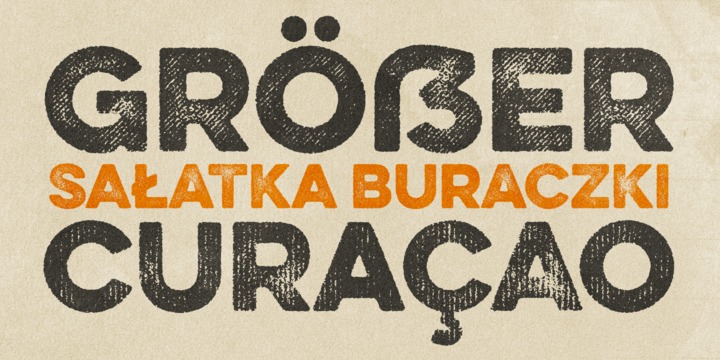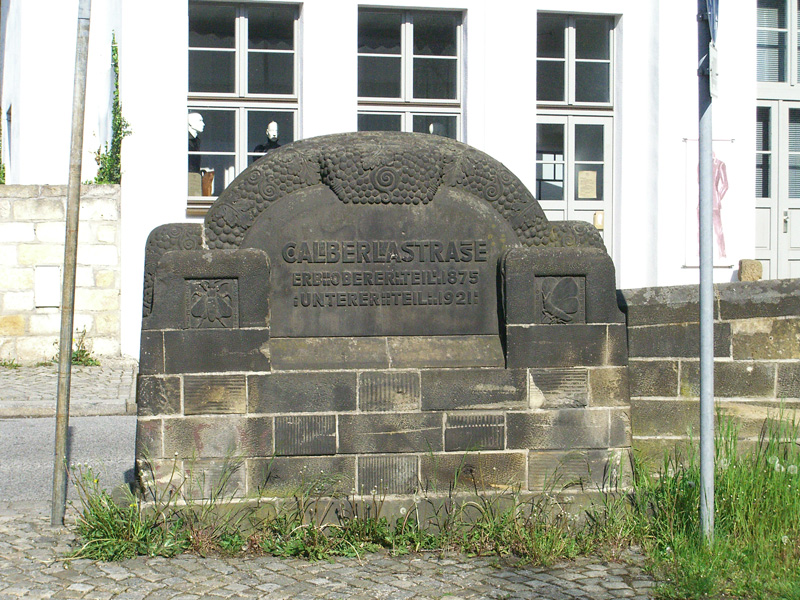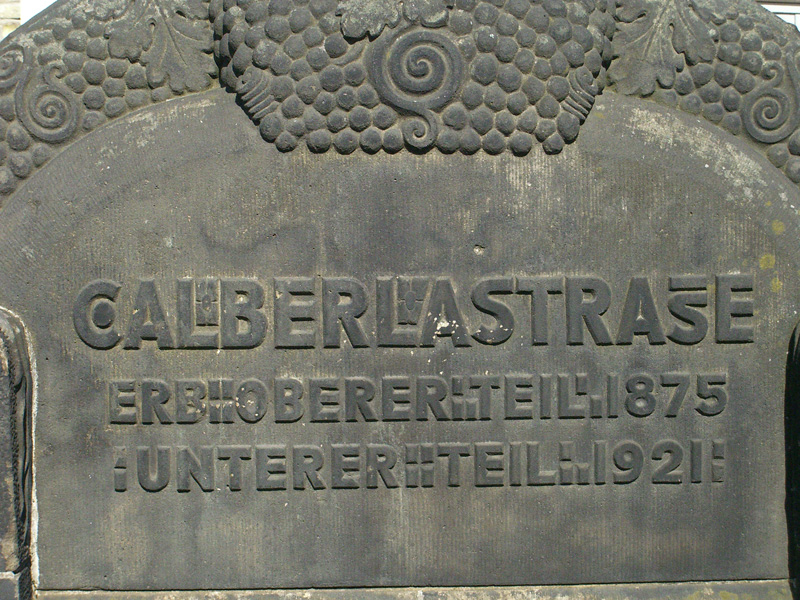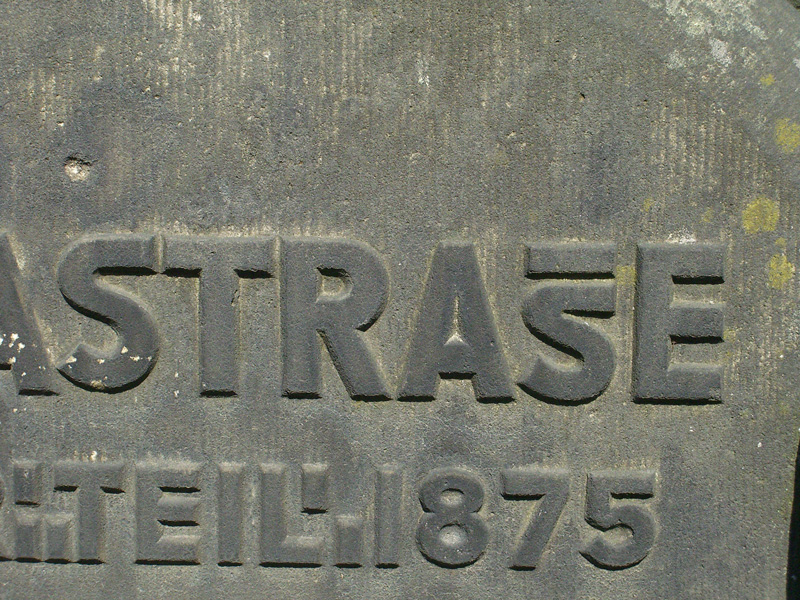
Liegt aber auch nur auf dem ß. Eine explizite ẞ-Glyphe hat er weiterhin nicht im Angebot. ;-)
Dieser Font enthält auch nur Versalien. ;-) Er hätte ja auch SS nehmen können, oder?  :shock::-o
Das würde von der Idee her, doch auch ein schönes VE abgeben (ohne dem Schwups vorne dran)  :nicken:
Bedarf es noch eines Beweises für die Notwendigkeit des ẞ zumindest für Eigennamen? Wenn ja, siehe Jens Weißflogs autobiografischer Bildband!
Anscheinend weil der Buchdeckel im Versalsatz gestaltet wurde, bekommt es selbst Weißflogs Verlag nicht mehr auf die Reihe, den Buchtitel für den gemischten Satz korrekt zurück zu übersetzen. So werden wir also mit folgendem Kuriosum konfrontiert:
Weissflog - Bilder meines Lebens      Jens Weißflog
das ß der aufrechten essay bereitet mir persönlich wenig freude:
für meinen geschmack zu handschriftlich-kalligrafisch – erinnert mich an das der alten dolly:
das wurde dann durch ein ruhigeres, größeres ß ersetzt, als die pro-version kam.
Aha? Da die handschriftlich-kalligrafische Betonung offenbar zum Konzept der Essay gehört, hat es mich gar nicht so gestört. Aber Danke für Deine immer wieder gern gelesene Analyse! :-)
Falls Du auch noch ein paar Gedanken zur Antithesis mit uns teilen möchtest, immer raus damit! ;-)
Hatten wir das hier schon mal? Kika erklärt das (große) Eszett (Video)
Bei der Gelegenheit ist mir dazu aufgefallen, dass Youtube nach wie vor ziemlich leer ist, was dieses Thema betrifft. Das hier war ja schon mal die richtige Einstellung. ;) Schon fast bisschen peinlich, dass bisher das Feld dem Kinderkanal allein gehört. ^^ (Gab’s da nicht auf Vimeo paar Inhalte die eigentlich mal auf Youtube mit um-/einziehen könnten?)
Das Filmchen wurde hier bestimmt schon mal gezeigt. Ich kenne es natürlich, aber sehe keinen Grund es zu »promoten«. Die geschilderten Geschichtshintergründe werden als Fakt verkauft, obwohl sie sehr strittig sind und das eigentliche Argument (weil ß und ß Kleinbuchstabenligaturen sind) ist Blödsinn. Der Fakt stimmt (wahrscheinlich), aber man kann daraus nicht die im Video erwähnte Schlussfolgerung ziehen. Umlaute waren historisch auch erst reine Kleinbuchstabenverschmelzungen. Ja, und? Das sagt über den Bedarf und die Konvention bezüglich der entsprechenden Großbuchstaben erstmal gar nichts aus.
Promoten würde ich das auch nicht. Beim Ansehen dieses (diesen?) Machwerks muss man sich ja schon fremdschämen. Außerdem ist mir das zu anti-versal-eszettig. ;) Ich dachte nur, ich werf’s mal in diesen Thread, weil ich letztens drüber gestolpet bin.
Habe es jetzt auch endlich mal geschafft, diese drei Aufsätze aus der Signa 9 zu lesen. Dort ist ja echt alles gesagt. Punkt. Wer dann immer noch gegen das Versal-ß schreit, der hat ja wohl den Schuss nicht gehört! :hammer:  ;) Die Zeit ist überreif, der Buchstabe gehört endlich eingeführt, basta. ;) Dass er „schön“ aussieht – im Duktus der Schrift und als Einzelform – ist die Aufgabe der heutigen Schriftgestalter. Dann klappt’s auch mit der Akzeptanz und der Anwendung „beim Volk“™. ;)
Die Macher des Videos „Kika erklärt das (große) Eszett“ sollten die „Empfehlungen und Hinweise für die Schreibweise geographischer Namen“ des Ständigen Ausschusses für geographische Namen (StAGN) lesen.
Wobei die Kika-Sendung von 2009 ist, die StAGN-Vorgabe von 2010.
Wie die Vorgabe der »amtlichen Schreibung« zu verstehen ist, darüber kann man sicherlich streiten. »Amtliche Kartenwerke« fallen in jedem Fall darunter, aber es ist ja auch von »anderen Veröffentlichungen für den internationalen Gebrauch« die Rede. Was fiele wohl alles darunter? Und wie verträgt sich das mit der »amtlichen Rechtschreibung«?
Nur bisschen zum entertainen:
Mir ist letzten Sonntag mein erstes historisches Versal-ß in freier Wildbahn begegnet. ;) In Dresden auf der Calberlastraße.
Oh Mann, sieht das sche!ße aus … ^^
Ich weiß nicht von wann der Stein genau ist, aber für die Melhuth’sche / Dresdner Form hat’s da scheinbar noch nicht so richtig gereicht. ^^
Haha, hätte mich eigentlich auch fast gewundert, wenn das hier noch nicht erschienen wäre. ;)
Aber es ist ja sowieso scheinbar gar kein Versal-ß … sondern ein Verdoppelungsstrich über einem verkleinerten Großbuchstaben. ^^ Alles Fake! *pah*  =D